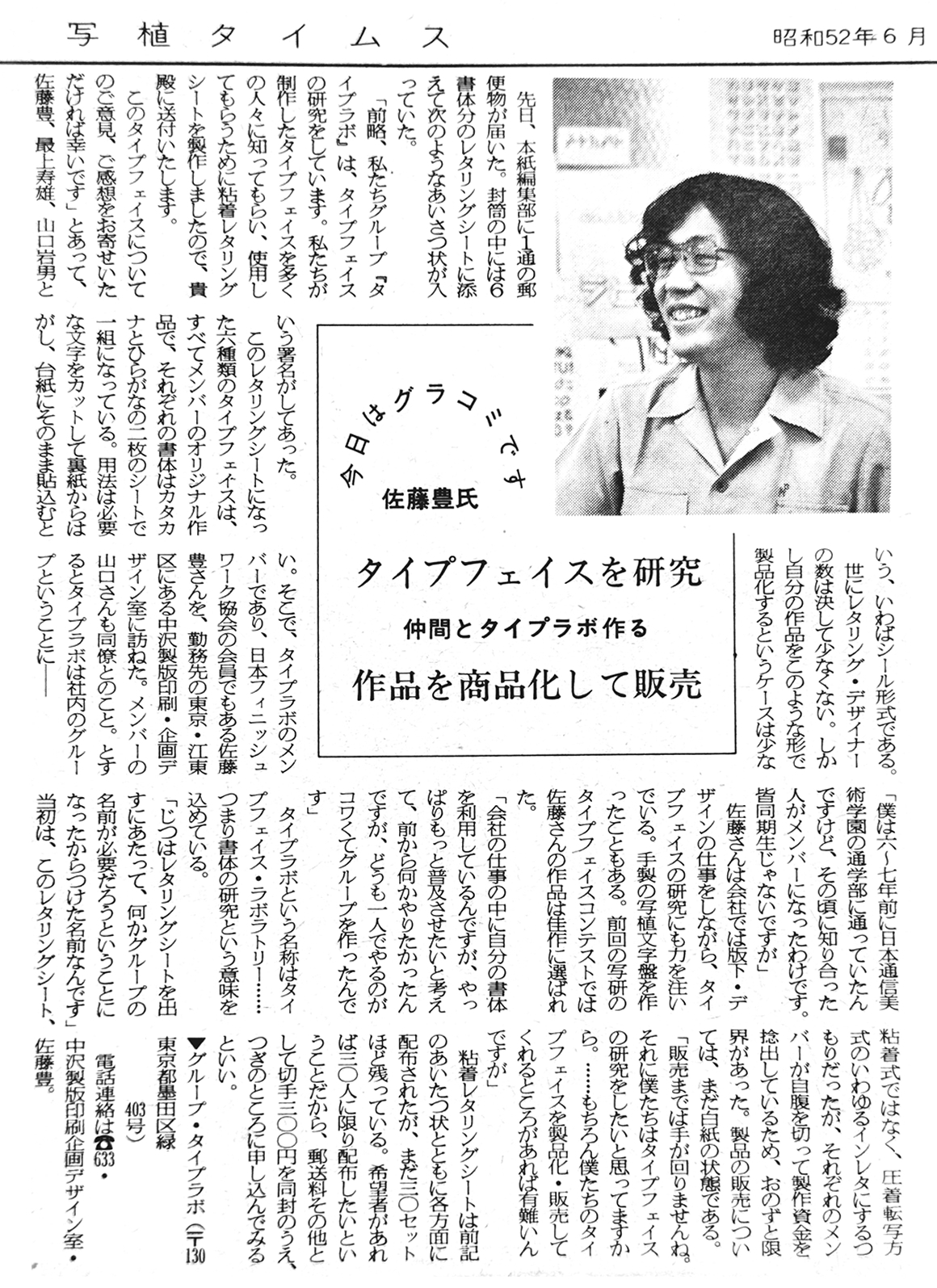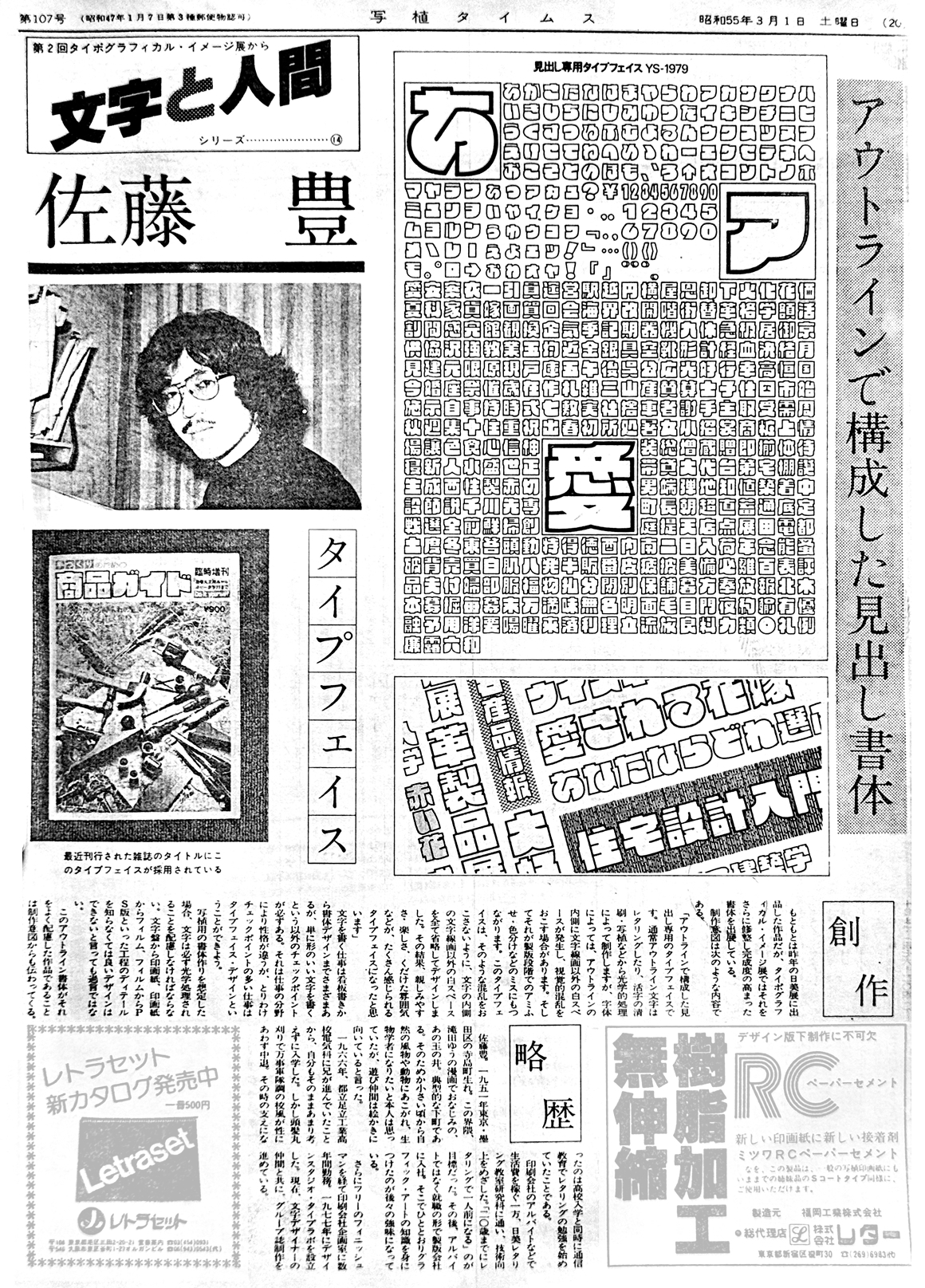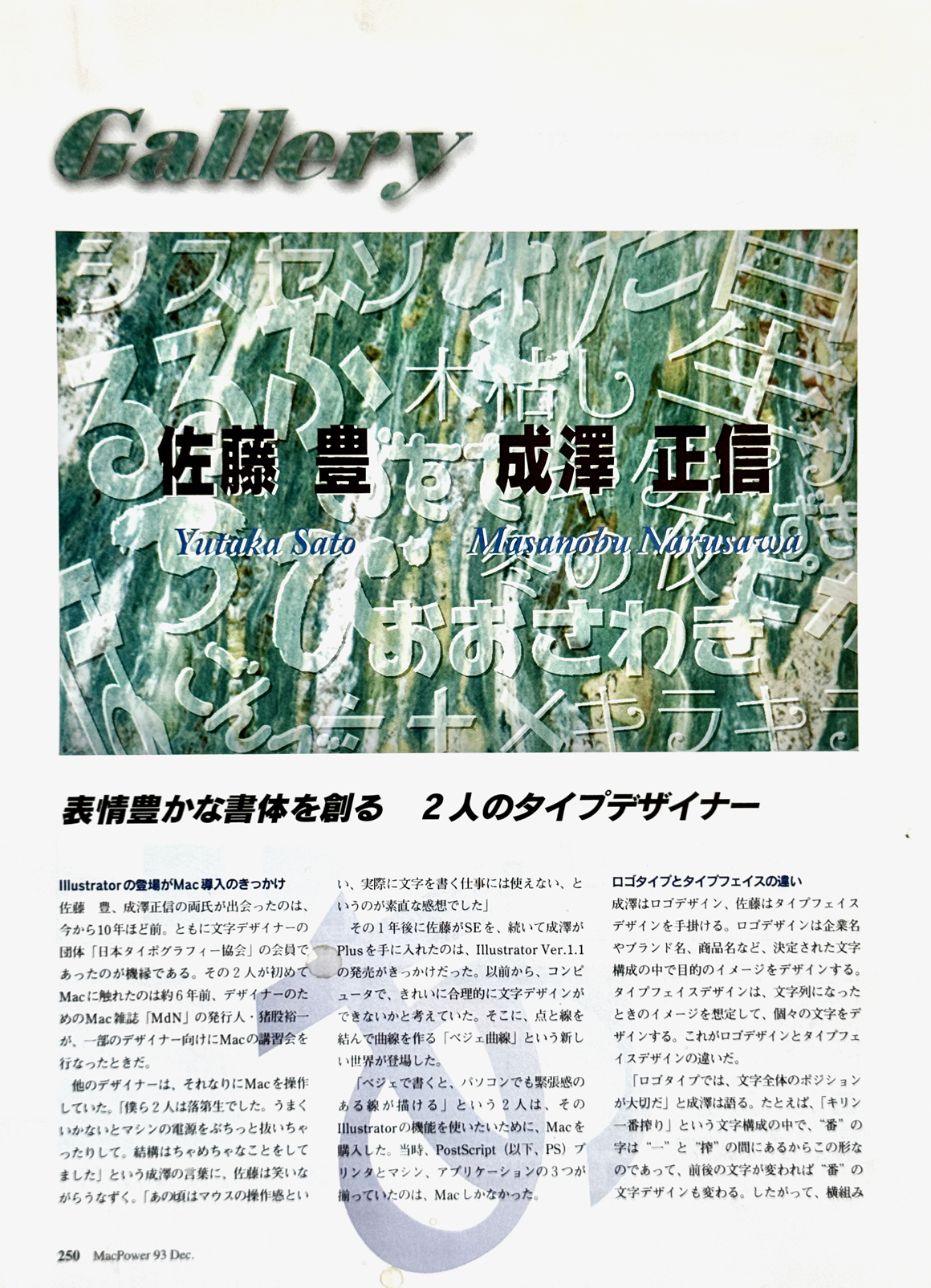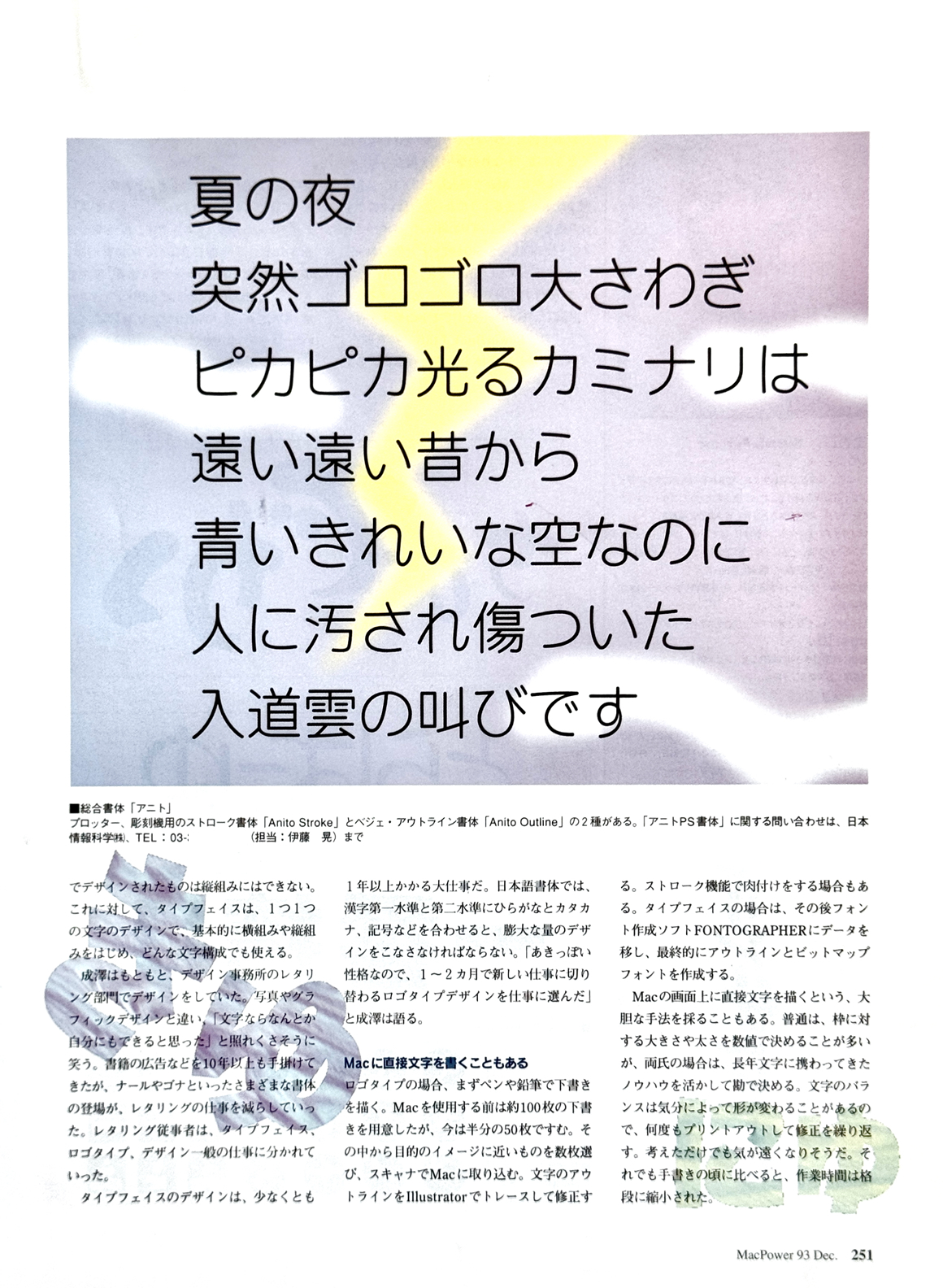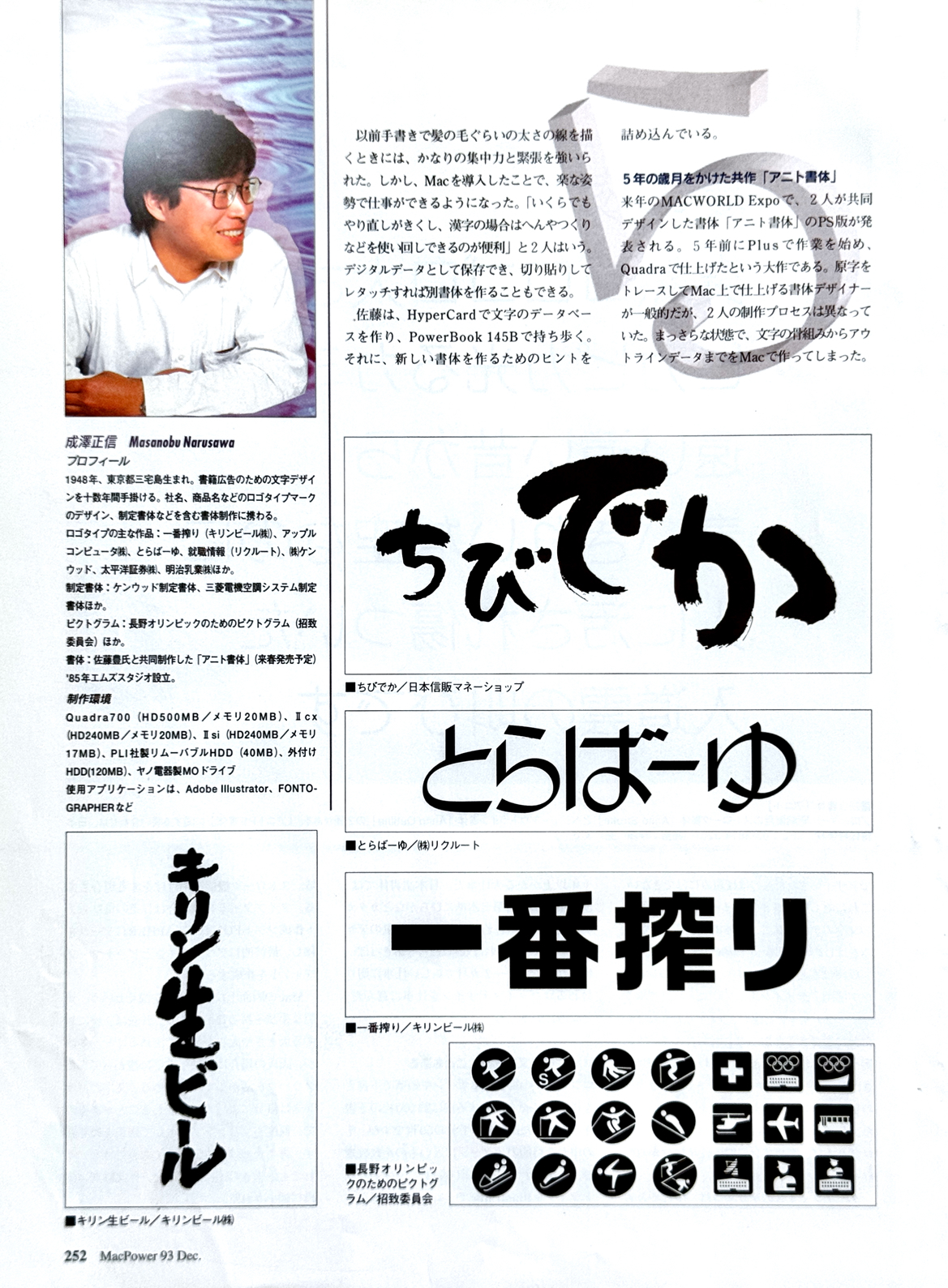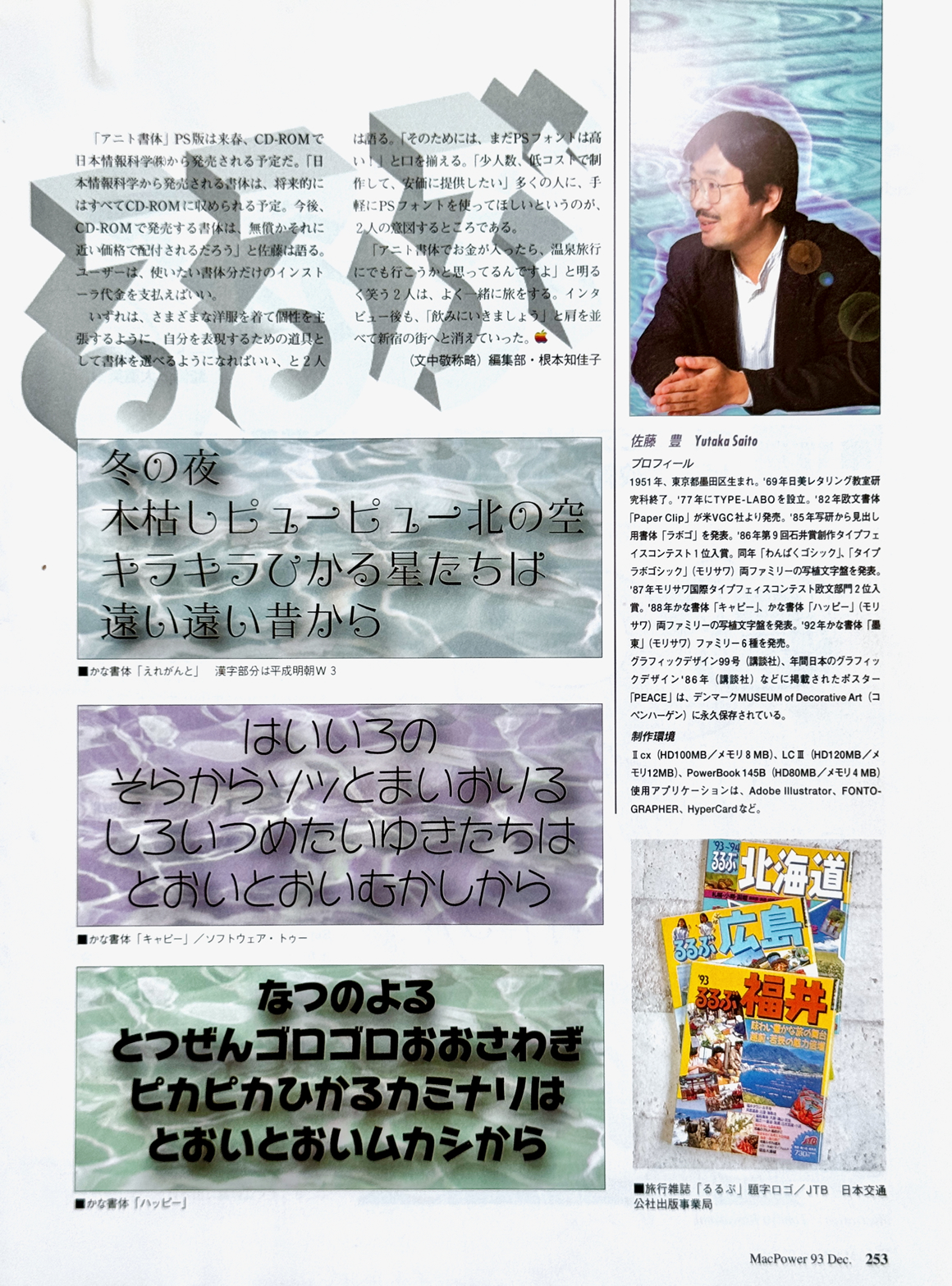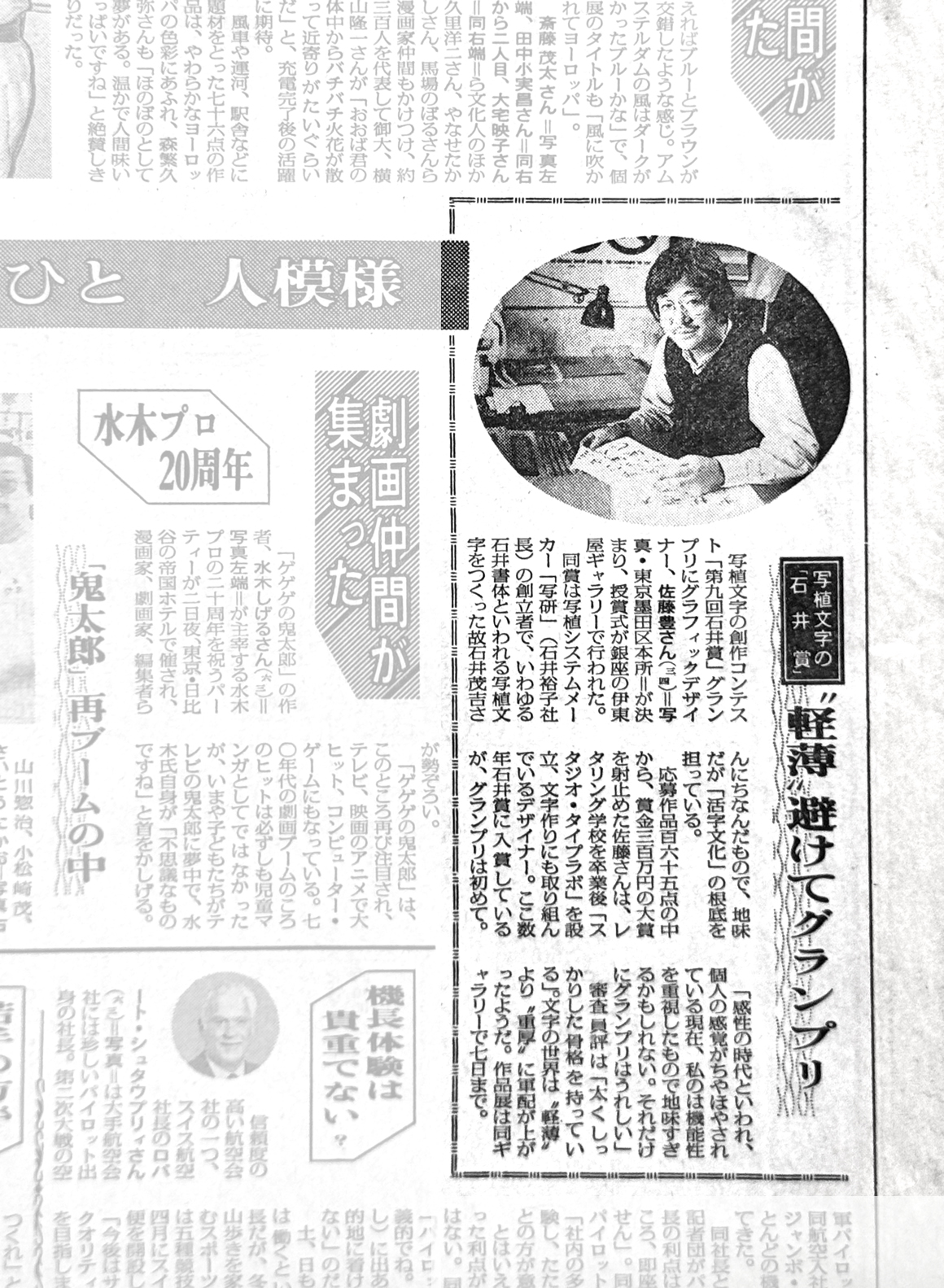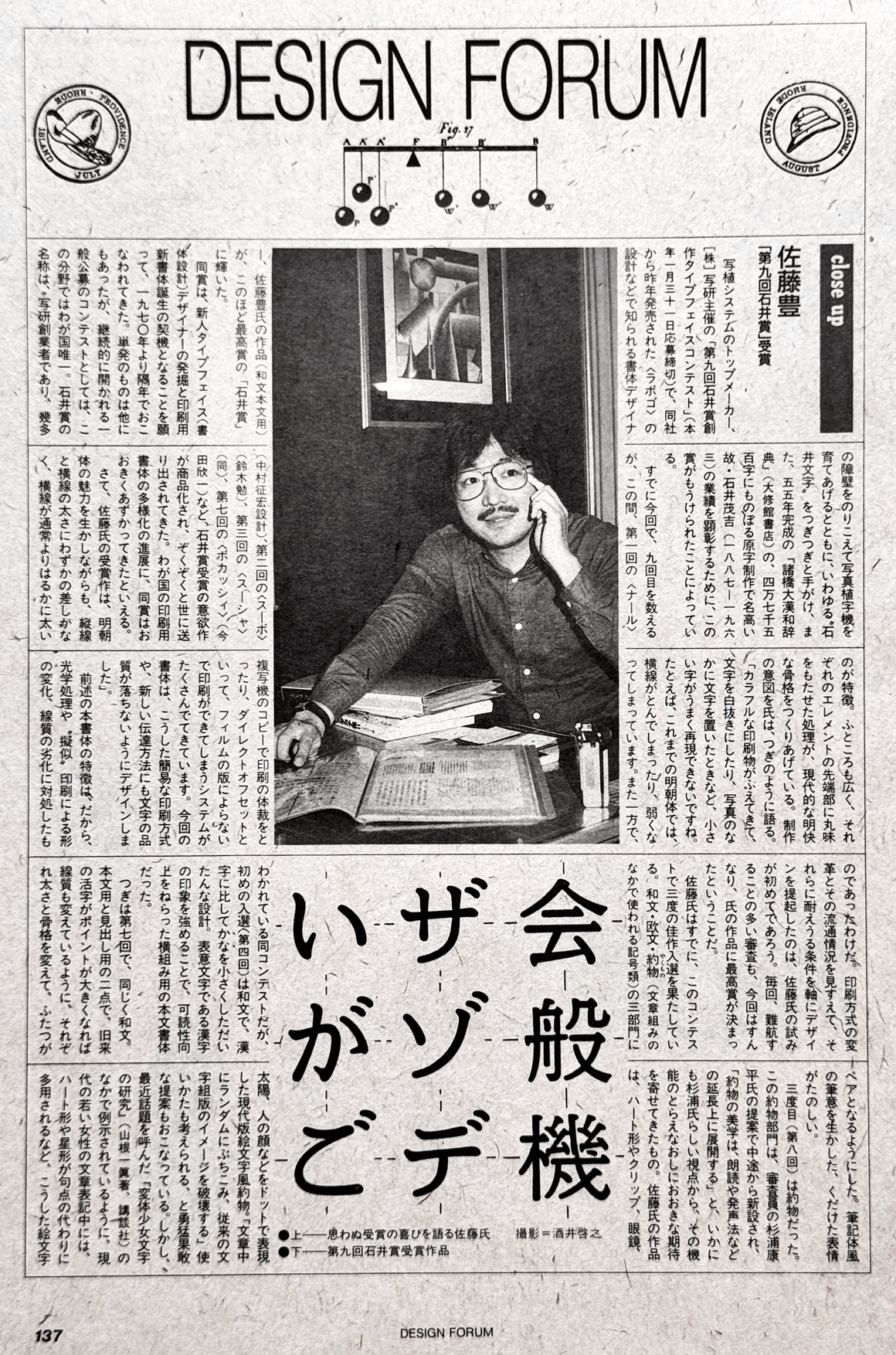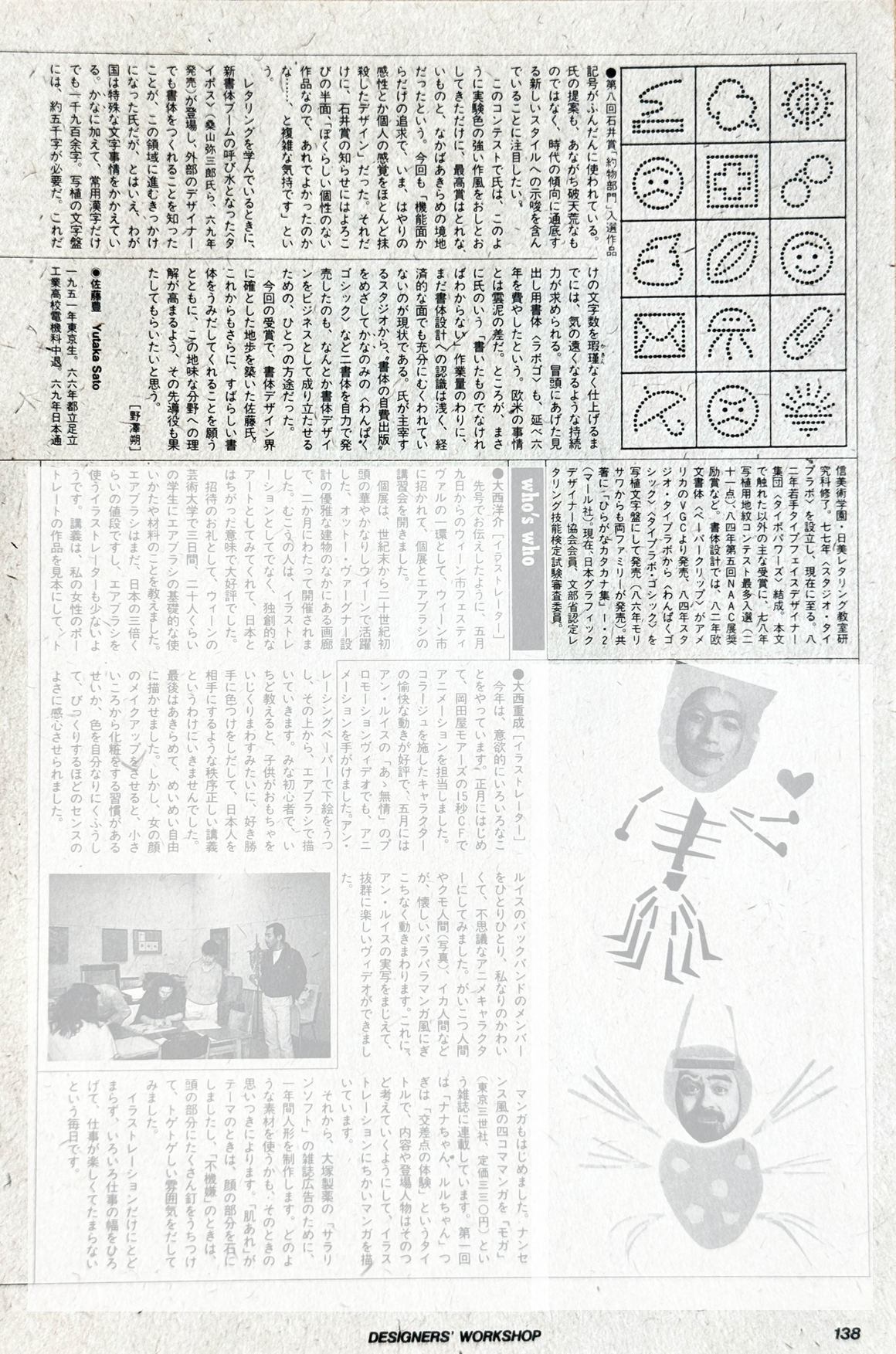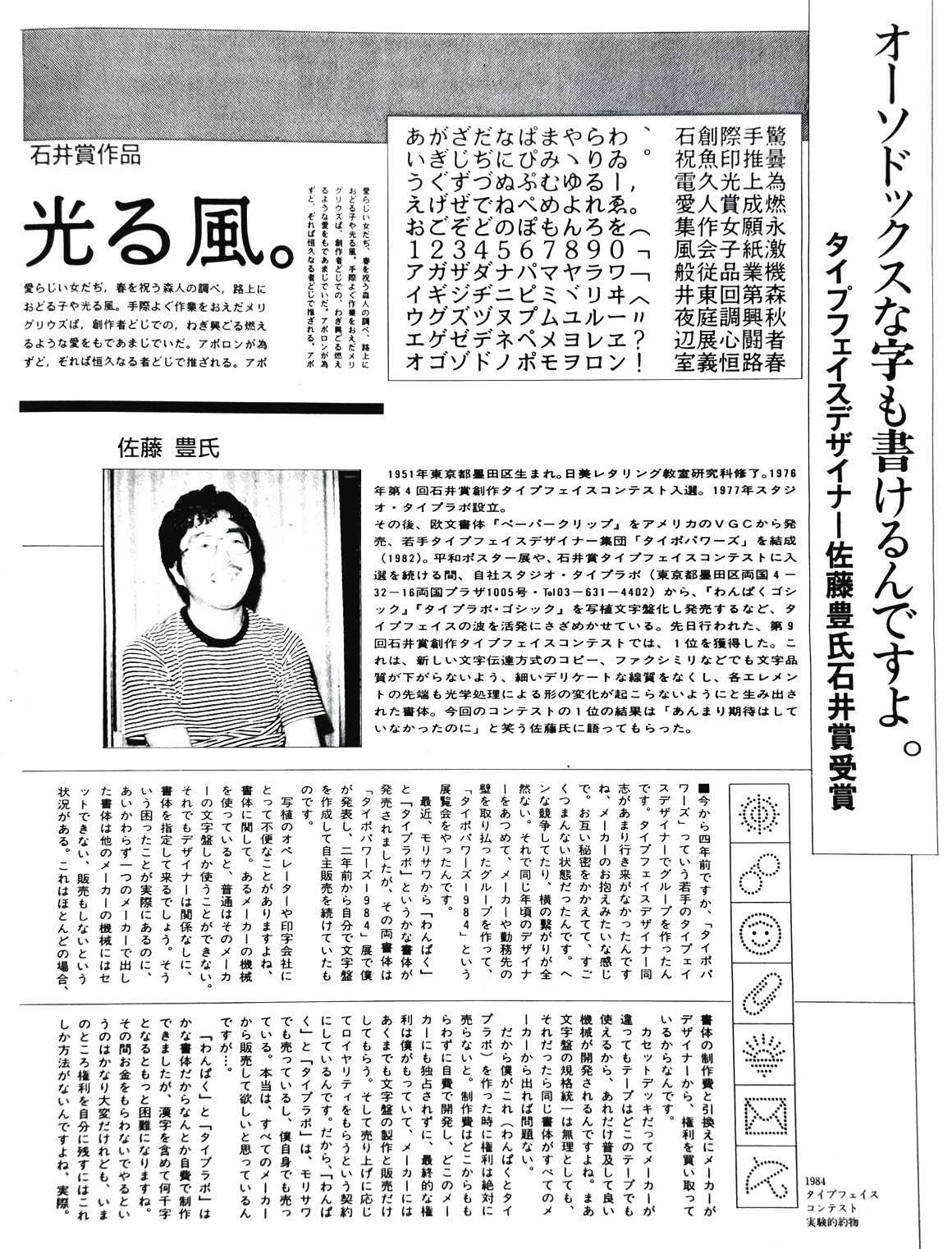
過去に話したことや書かれた記事を…そのままリアルな画像で紹介するページ(1975〜1986)
思わず、一人でニンマリ(1975) 36回スタジ紙上展金賞
日本通信美術学園では、レタリングを勉強中の生徒や卒業生を対象にしたコンテストが随時開催されていて、スタジオ紙上展は年に4回開催されていた。
文字に賭けた青春(1976) スタジオ紙417号
スタジオ紙は、日本通信美術学園がレタリングを勉強中の生徒や卒業生を対象に発行していた機関紙。月に3回発行されていた。
使って貰わなければ(1977) スタジオ6号
この頃は、日本通信美術学園で学んだ仲間とタイプフェイス研究グループを作って活動していた。
作品を商品化して販売(1977) 写植タイムス6月号
グループ・タイプラボで、レタリングシートというフォント商品を通信販売していた。
もう根性ですよね(1977) スタジオ556号
科学技術館で毎年行われていた印刷機材展で催されたタイポグラフィカルイメージ展に参加。
私はYS-1979(後のラボゴ)を出品した。
アウトラインで構成した見出し書体(1977) 写欲タイムス3月号
YS-1979(後に写研から発売されるラボゴ)についての記事。
表情豊かな書体を創る2人のタイプデザイナー(1983)
1982年に日本タイポグラフィ協会に加入し、成澤正信氏と知り合いアニト書体を共同制作した。
「NAAC展」奨励賞!(1984) 日本通信美術学園 学園ニュース「私の仕事」
日本広告技術協議会の「NAAC展」で奨励賞、石井賞コンテストの約物部門で佳作入選、写植文字盤の自主販売などが紹介された。
第9回石井賞で1位(1986) 写研PR誌「QT」67号
このコンテストの主催者である写研のPR誌「QT」に掲載された記事。
第9回石井賞で1位(1986) 毎日新聞7月4日夕刊
石井賞受賞に関する新聞記事、この他に読売とか朝日にも同様の記事が掲載された。
佐藤豊「第9回石井賞」受賞(1986) デザインの現場8月号
石井賞受賞に関するデザイン誌の記事、石井賞受賞のことや前回の約物部門で入選した実験的作品が紹介された。
オーソドックスな字も書けるんですよ(1986) 写植タイムス8月号
石井賞受賞、実験的約物、欧文書体、ラボゴ、かな書体などが掲載された。
たゆまぬ努力が実って最高賞獲得(1986) 学園ニュース9月号
石井賞受賞に関する記事、モリサワから発売された「かな書体」などが掲載された。
第九回石井賞 佐藤豊(1986) 美術手帖9月号
石井賞受賞受賞や文字盤の自主販売などの記事。